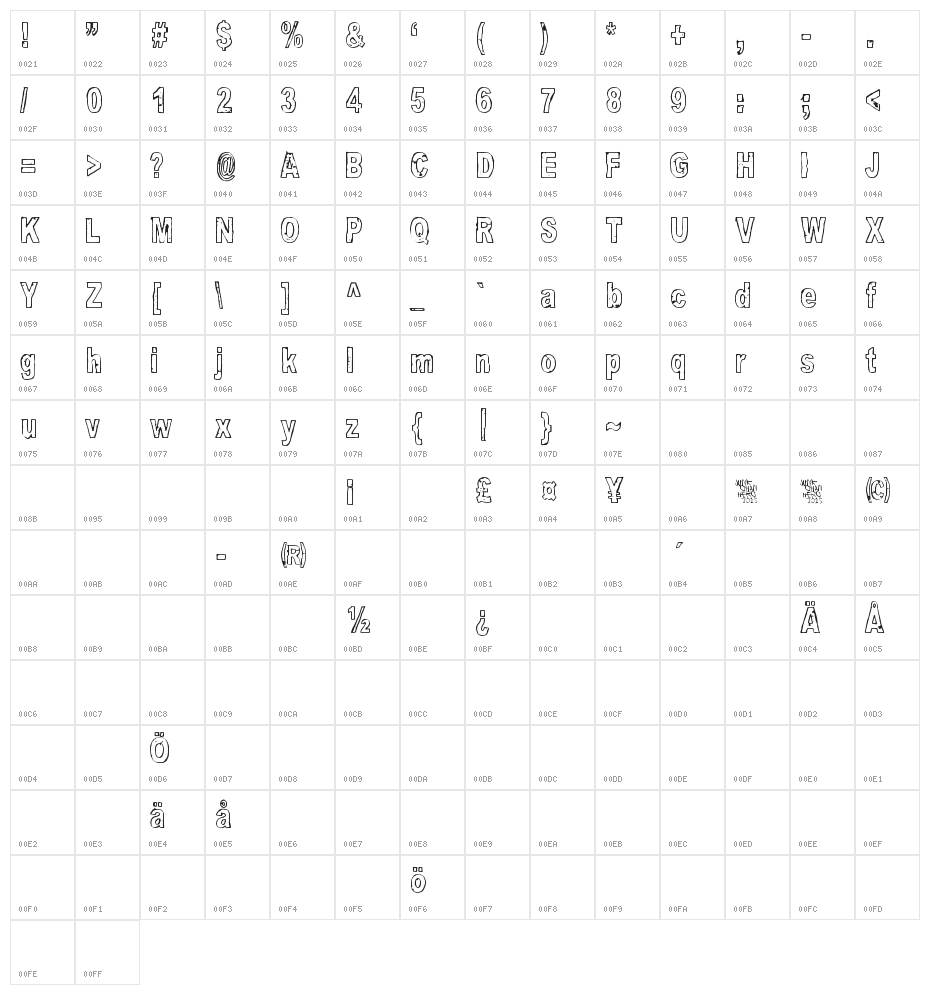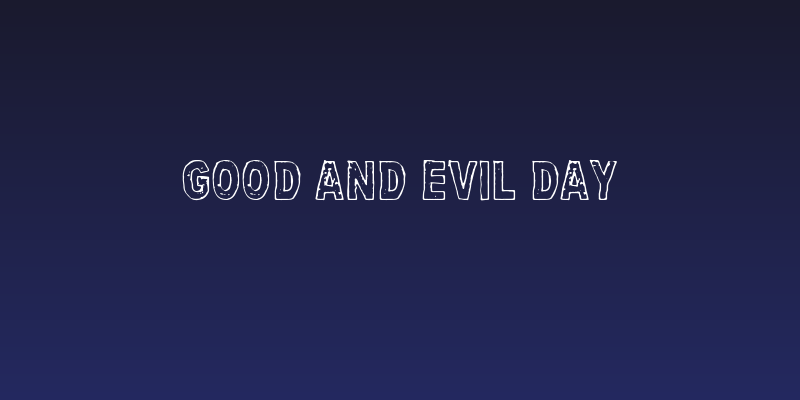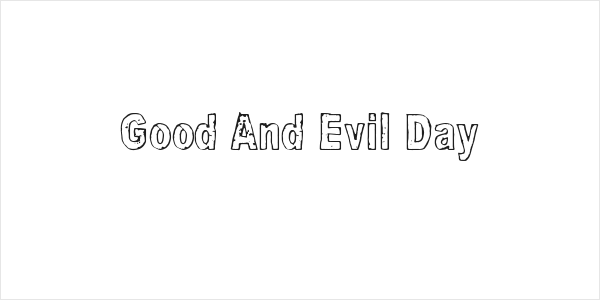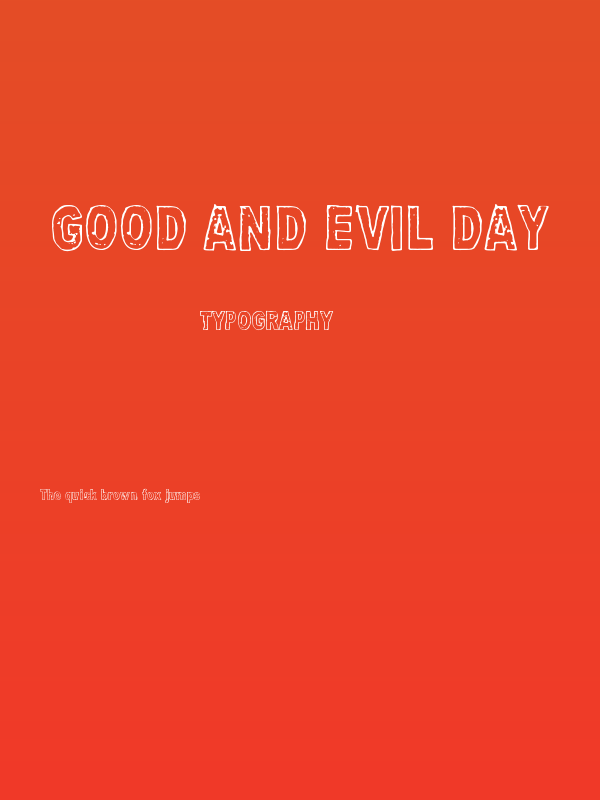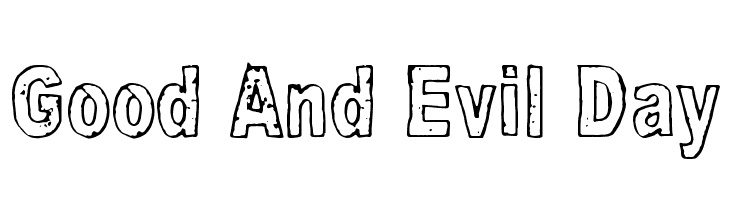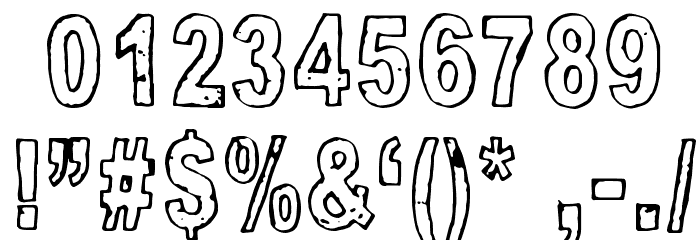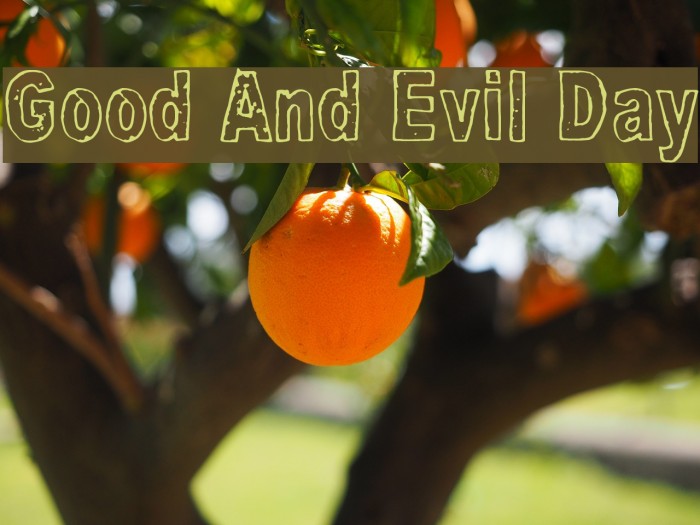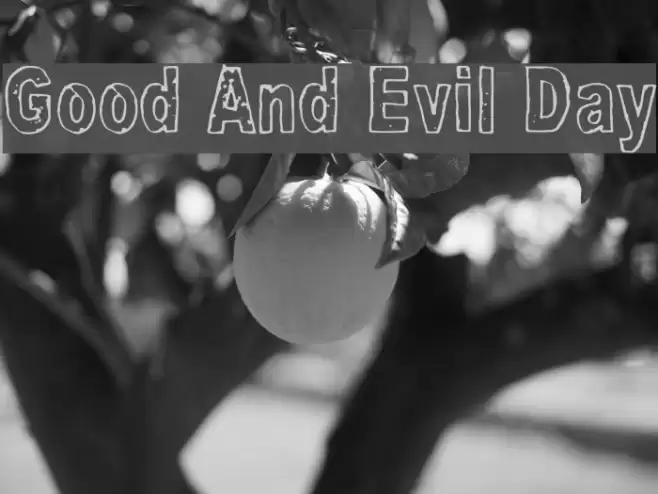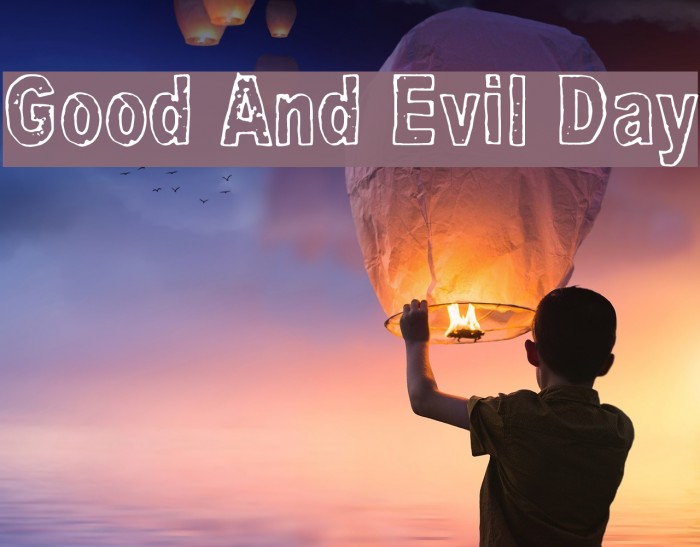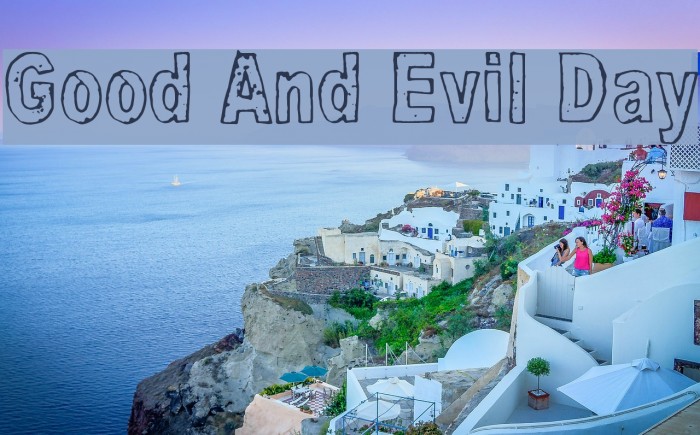
Good And Evil Day Font
✎ Distorted Eroded
| おすすめプロジェクト | Ideal for projects that require a rustic or vintage feel, such as posters, album covers, or branding for artisanal products. |